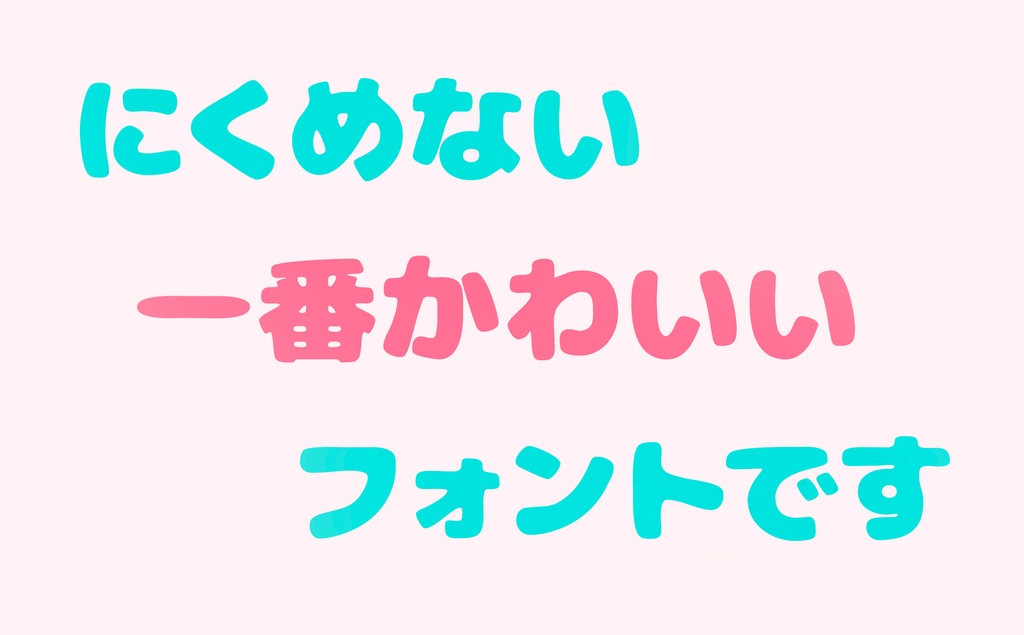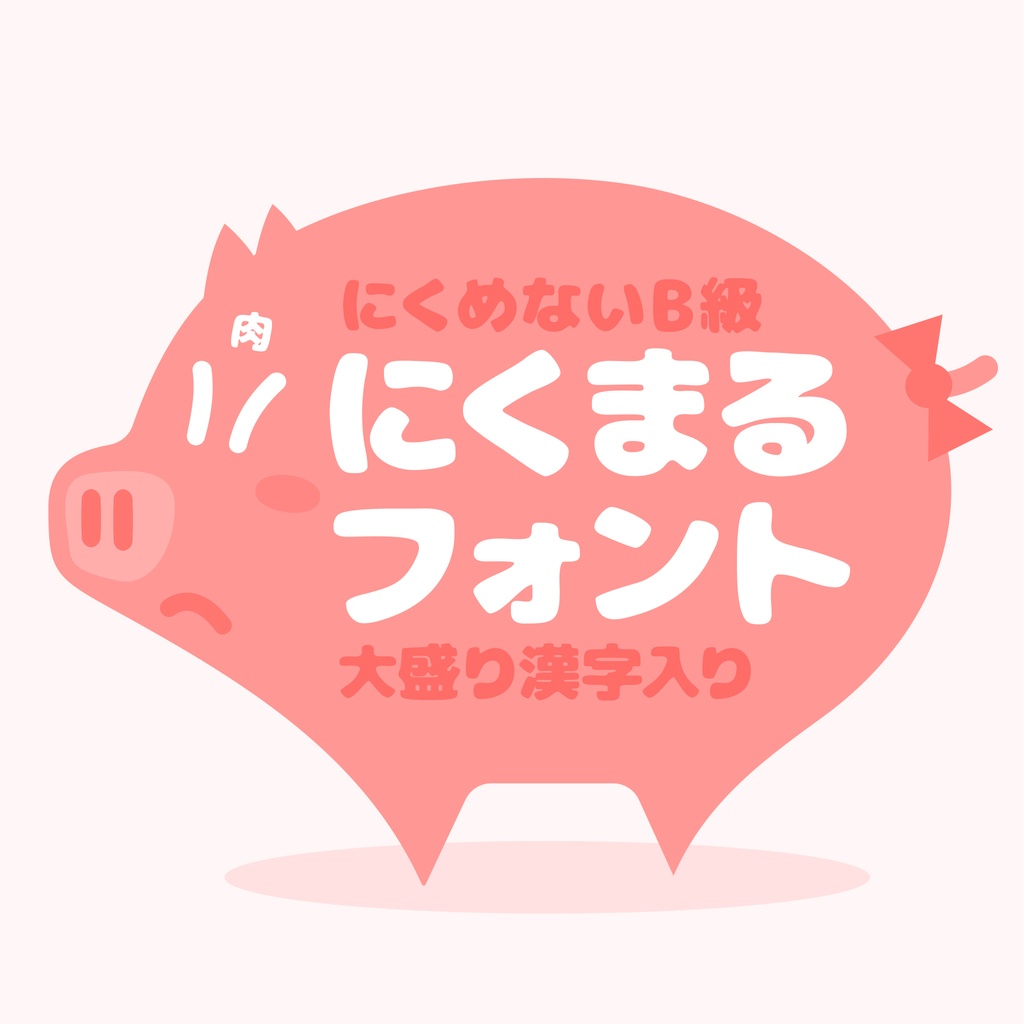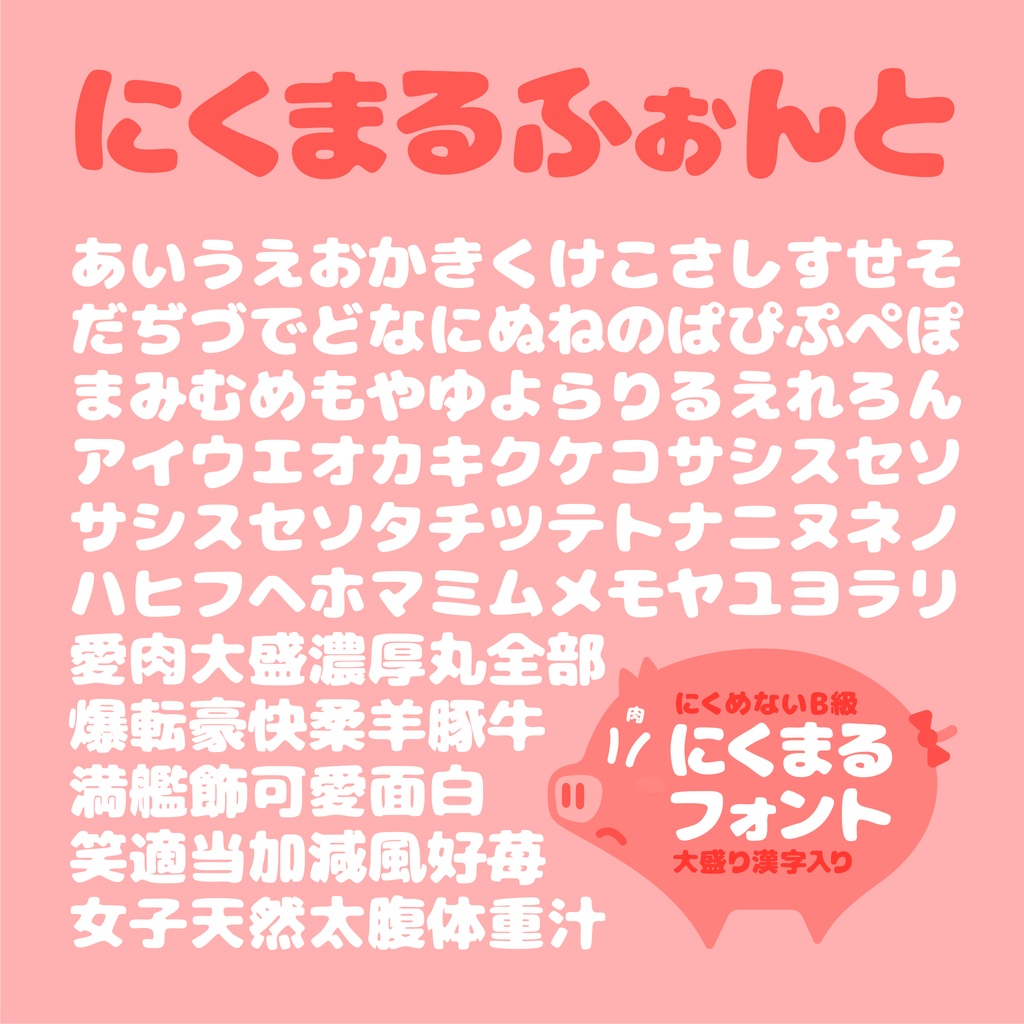
にくまるフォント
にくまるフォントはどんなフリーフォント? フリーフォントのにくまるフォントは無料でダウンロードできる書体。商用・非商用問わず使用可能なので、安心してダウンロードしてください。ロゴデザインやタイトルロゴ、見出し向けの漢字も含まれる日本語フリーフォントになります。ゆるくて、てきとうな、柔らかい雰囲気が特徴のフォントです。美しさや、正確さとは無縁ですが、デザインに素人っぽい楽しさを加えます。 microsoftのエクセルやワードなどお手持ちのソフトでご使用できます。Adobeのグラフィックソフト(イラストレーター、フォトショップ)があればアウトライン化などし編集して、よりお楽しみ頂くこともできると思います。 このまるまる太った可愛くて憎めないフォントを 自由に、たのし〜く使っていただけると、すごく嬉しいです。 ■にくまるフォントのライセンス フォントは以下のライセンスに準じます。フォント同梱のテキストをお読み下さい。 * M+ (LICENSE_J,LICENSE_E) Copyright(c) 2014 M+ FONTS PROJECT このフリーフォントをご使用になるには、ダウンロードファイルに含まれる 「M+FONT-TESTFLIGHT」の内容を読みください。 It is requested to read and accept “M+FONT” before downloading Font. ■フォントの商用利用・プログラムへの埋め込みについて 作成した印刷物およびデジタル・コンテンツにつき、その商用・非商用にかかわらず 放送、通信、各種記録メディアなどの媒体の形式も問わず、使用をすることができます。 ただし、これはM+のライセンスのもとにあります。 M+ フォント製作者の皆様ありがとうございます。 ■にくまるフォント収録文字について・フォント形式について 数字、アルファベット、記号、かな文字(ひらがな・かたかな)、教育漢字、常用漢字 第一水準漢字、第二水準漢字(途中まで完成)、その他主要な多言語 OpenTypeフォントを収録(その他の用、旧OS用にTrueTypeも同梱) ■フリーフォント使用上の注意事項 紹介・説明する目的でのスクリーンショットやフォント画像のご使用はご自由に行って大丈夫です。ご安心ください。 フォントは、予告せず改良、変更、アップデートすることがあります。 フォントのダウンロード・導入はお客様の責任において行っていただきます。 規定した動作環境以外でのフォントの使用について、いかなる保証も行いません。 このフォントを使用したことにより発生したいかなる損害(データ損失等を含む)についても、作者や転載者は責任を負いません。 フォントの動作環境 ウィンドウズ:日本語版Windows 95〜11 マッキントッシュ:Mac OS X対応(10.x)~最新のOS ⚠️このフォントは自由に動画に使えるフォントです。ご利用の際は次のクレジットを入れていただけると、ものすご〜く喜びます! –––––––––––––––––––––––––––––– フォント:にくまるフォント フリーダウンロード:https://flopdesign.booth.pm/items/4571432 –––––––––––––––––––––––––––––– フォローしてください。 Instagram ▶ https://www.instagram.com/flopdesign.font/ X ▶ https://twitter.com/flopdesign